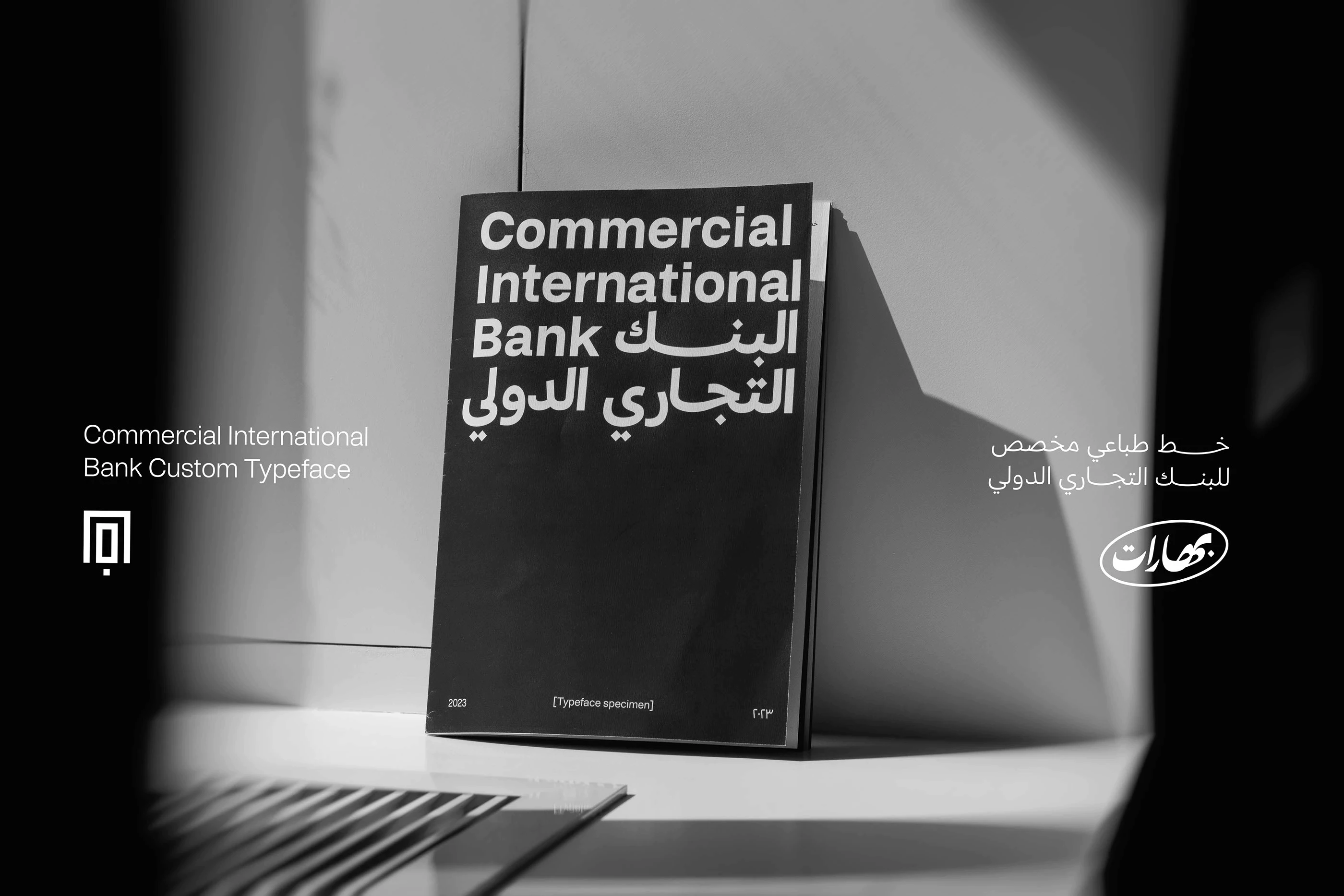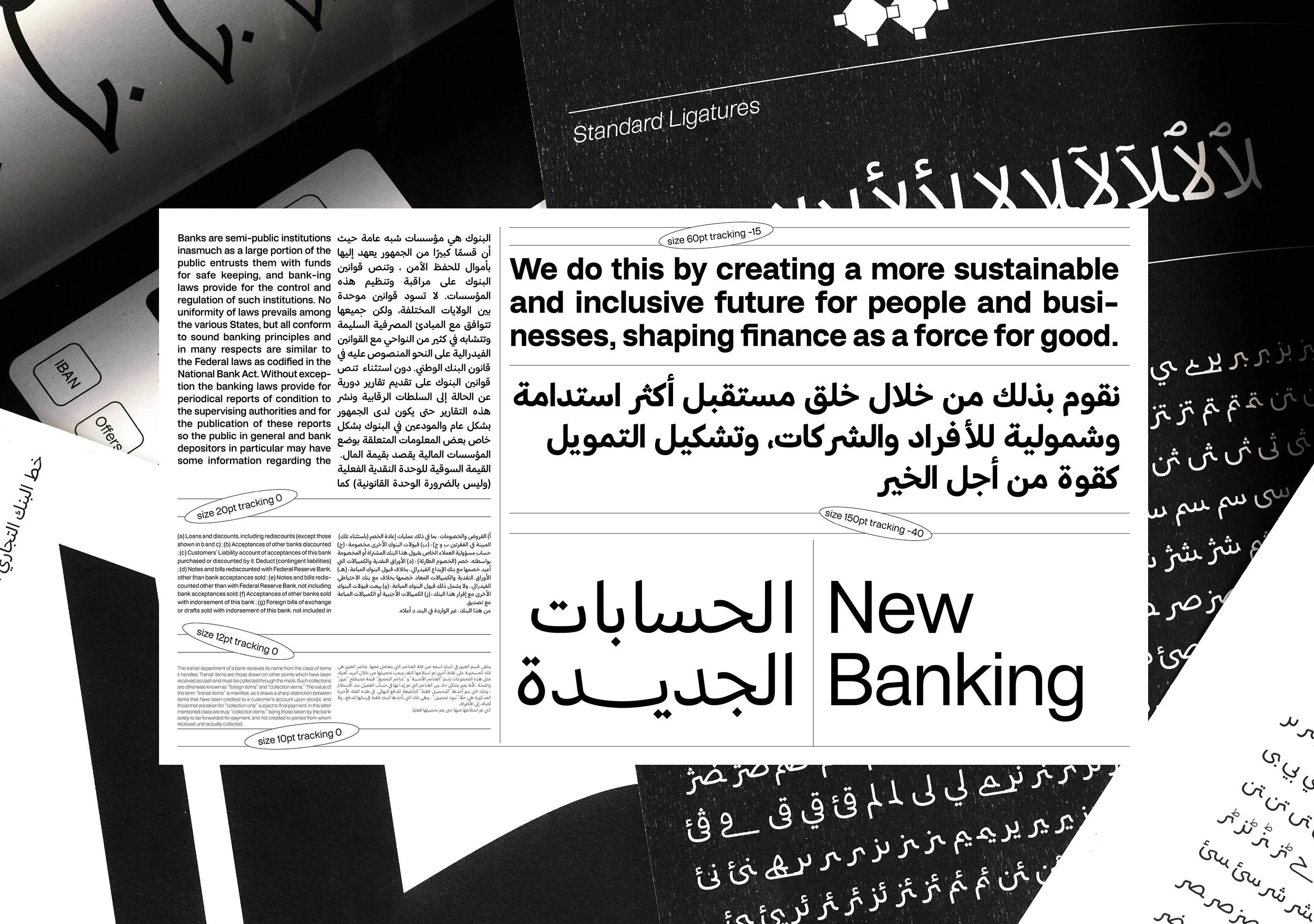
الخط متعدد الأنظمة المصمم لبنك CIB هو خط أحادي السماكة وخالٍ من الزوائد (سان سيريف)، ويتوفر بأوزان متعددة تشمل النسخ المائلة، مما يتيح استخدامًا مرنًا عبر وسائط مختلفة. يتميز خط CIB بسهولة القراءة ويصلح للنصوص الصغيرة، ومع ذلك يحتوي على سمات أسلوبية تجعله مناسبًا أيضًا لاستخدامات العناوين والعرض.